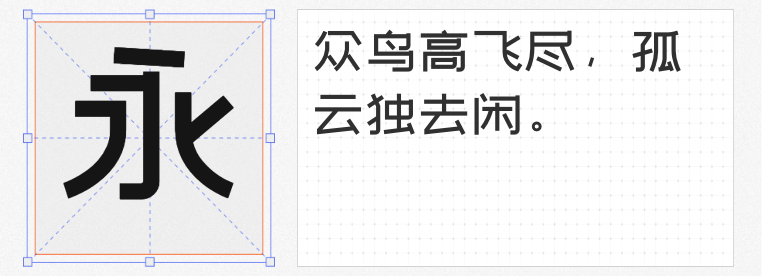
在包装设计的世界里,字体不仅是信息传递的载体,更是品牌个性的视觉语言。选择一款合适的免费商用字体,既能降低设计成本,又能提升作品的艺术表现力。以下四款字体,以独特的风格和免费商用的优势,成为包装设计的优质之选。
1. 斗鱼追光体2.0
作为斗鱼直播平台自主研发的品牌字体,这款字体以“活力、上进、娱乐”为设计核心,字形简洁流畅,笔画间透露出科技感与现代感。在包装设计中使用,能瞬间传递品牌的年轻态度与创新精神,尤其适合电子产品、运动品牌或潮流文化的包装表达。
2. 站酷文艺体
由设计师刘兵克操刀,以“文艺清新”为基调,字形略扁,笔画粗细统一,细节处融入圆角与曲直对比,既保留了传统书法的雅致,又兼具现代设计的简洁。这款字体在食品、文创或生活用品的包装上,能营造出温馨、自然的氛围,拉近与消费者的情感距离。
3. 站酷小薇LOGO体
以“剑身”为灵感,笔画修长灵秀,结构简约而不失识别性。这款字体突破传统字形框架,大胆创新的设计语言,使其在化妆品、珠宝或高端品牌的包装中脱颖而出,传递出精致、优雅的品牌气质。
4. 仓耳非白 W04
作为一款家族字体,仓耳非白以强烈的粗细对比和方整结构为特色,笔画转折处采用直角处理,同时融入圆形元素,刚柔并济。这种独特的设计风格,使其在酒类、茶叶或传统工艺品的包装上,既能展现文化底蕴,又能通过现代设计手法吸引年轻消费者。
这四款免费商用字体,各具特色,覆盖了从科技潮流到文艺复古的多元风格,能为包装设计提供丰富的创意选择。合理运用它们,不仅能提升作品的视觉冲击力,更能精准传递品牌价值,让产品在货架上一眼被看见。